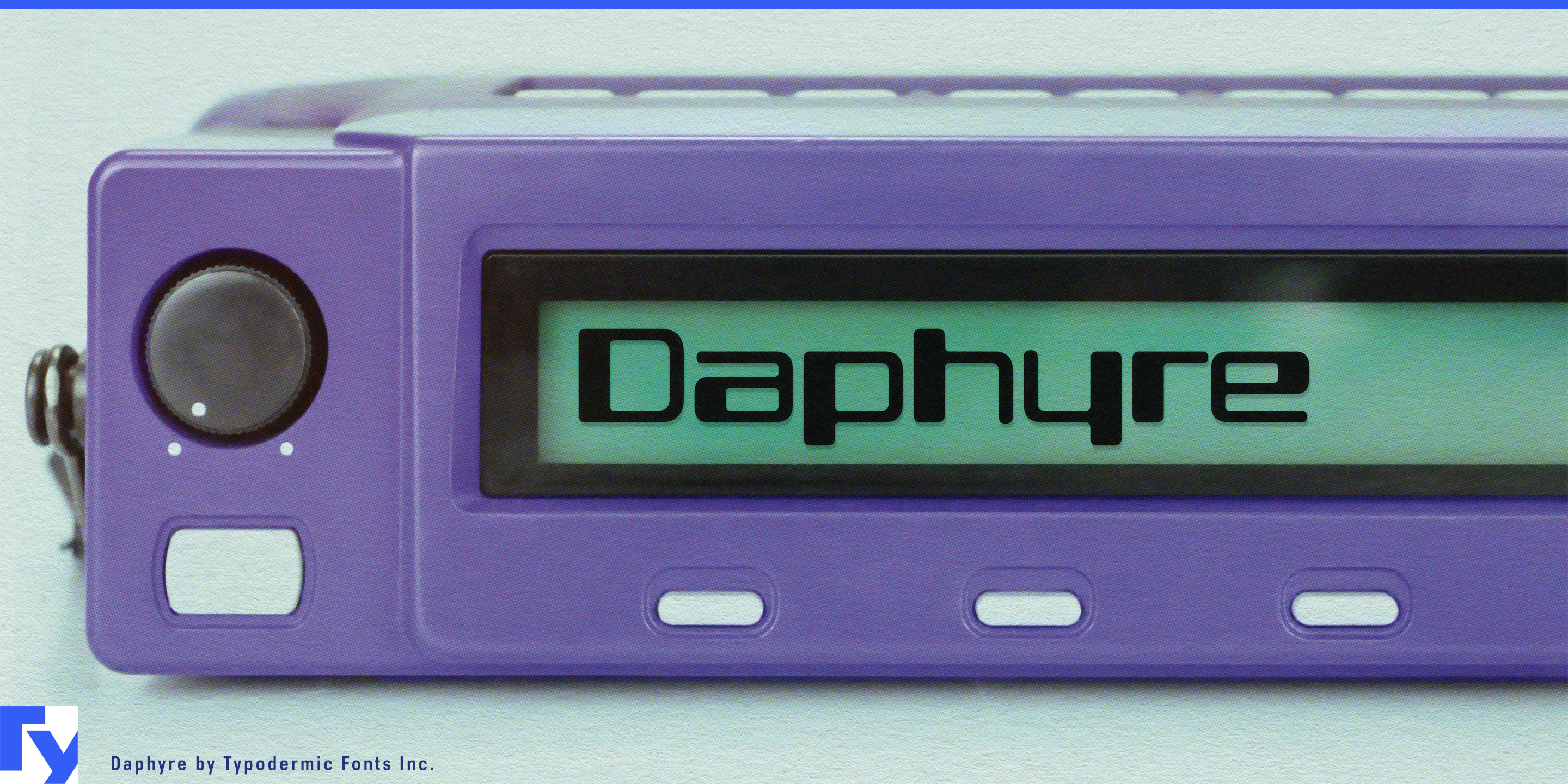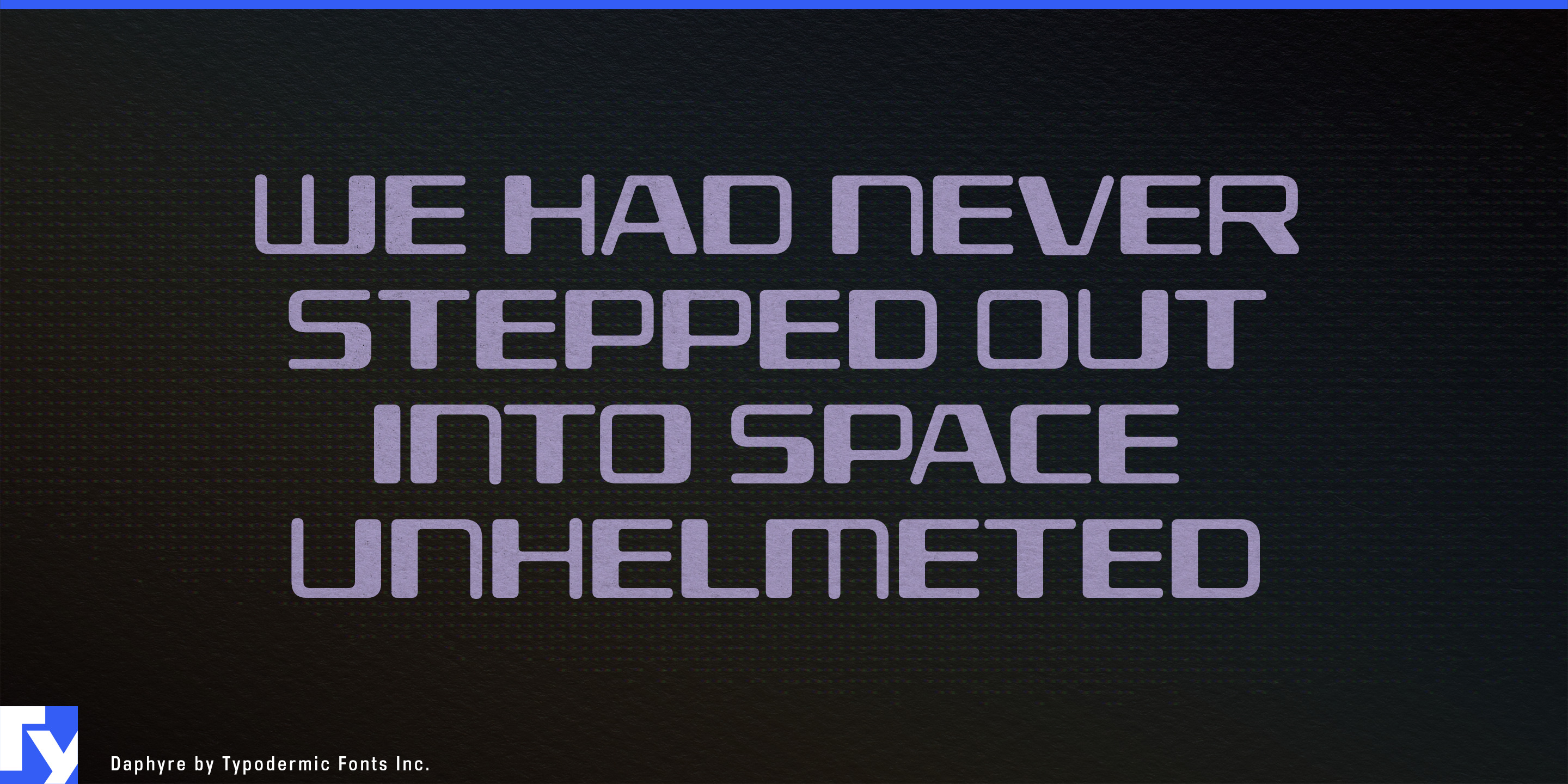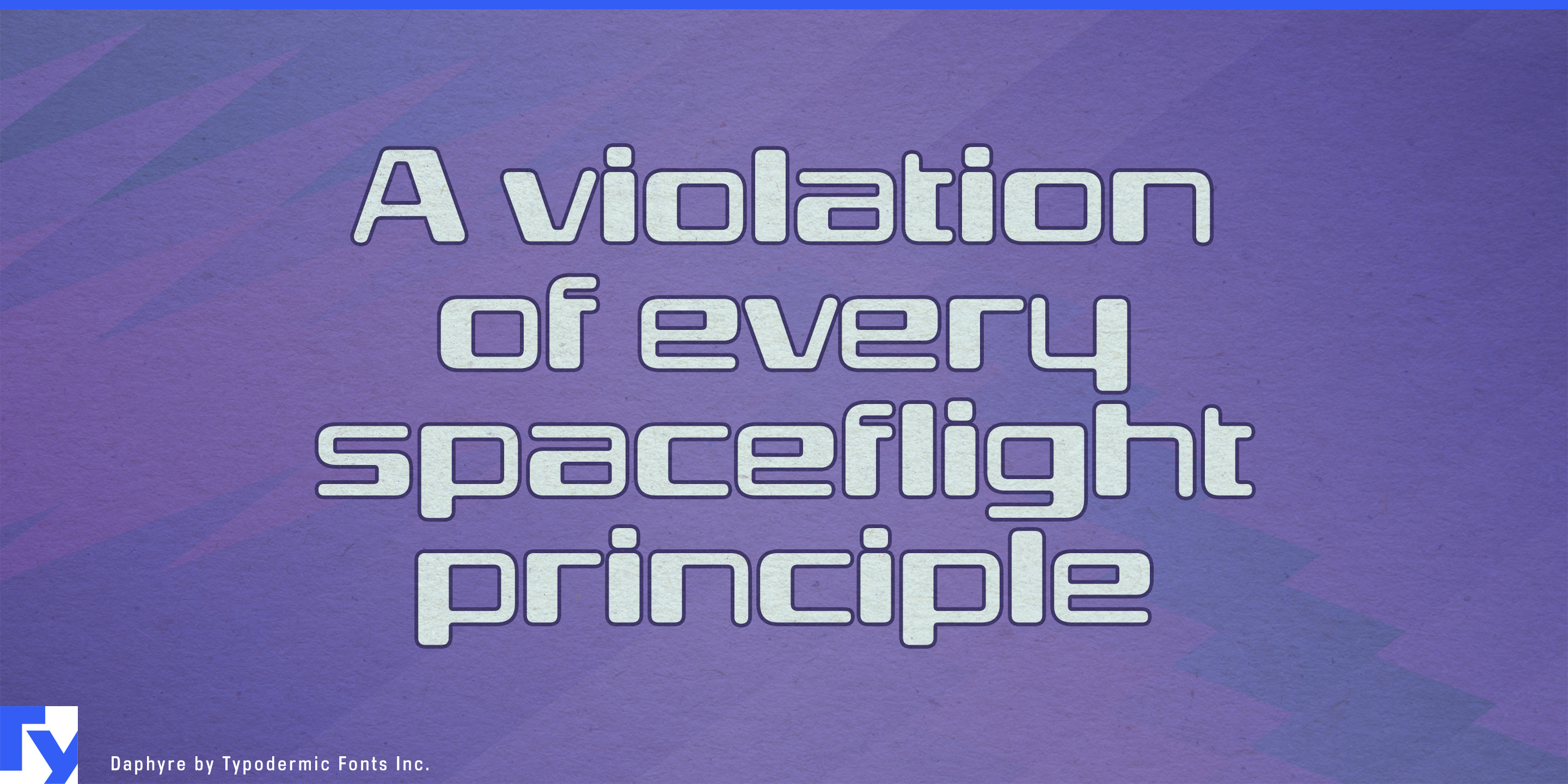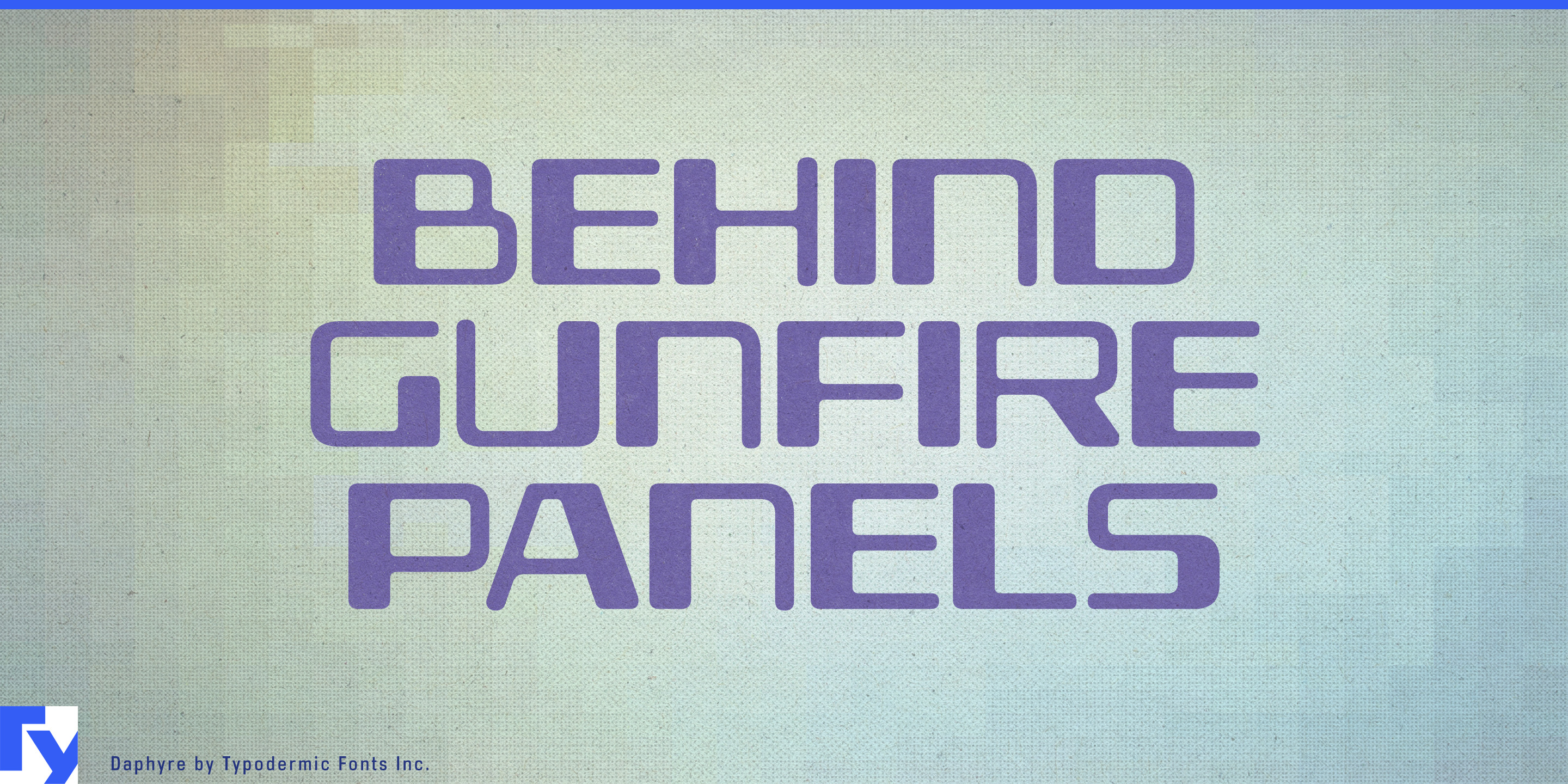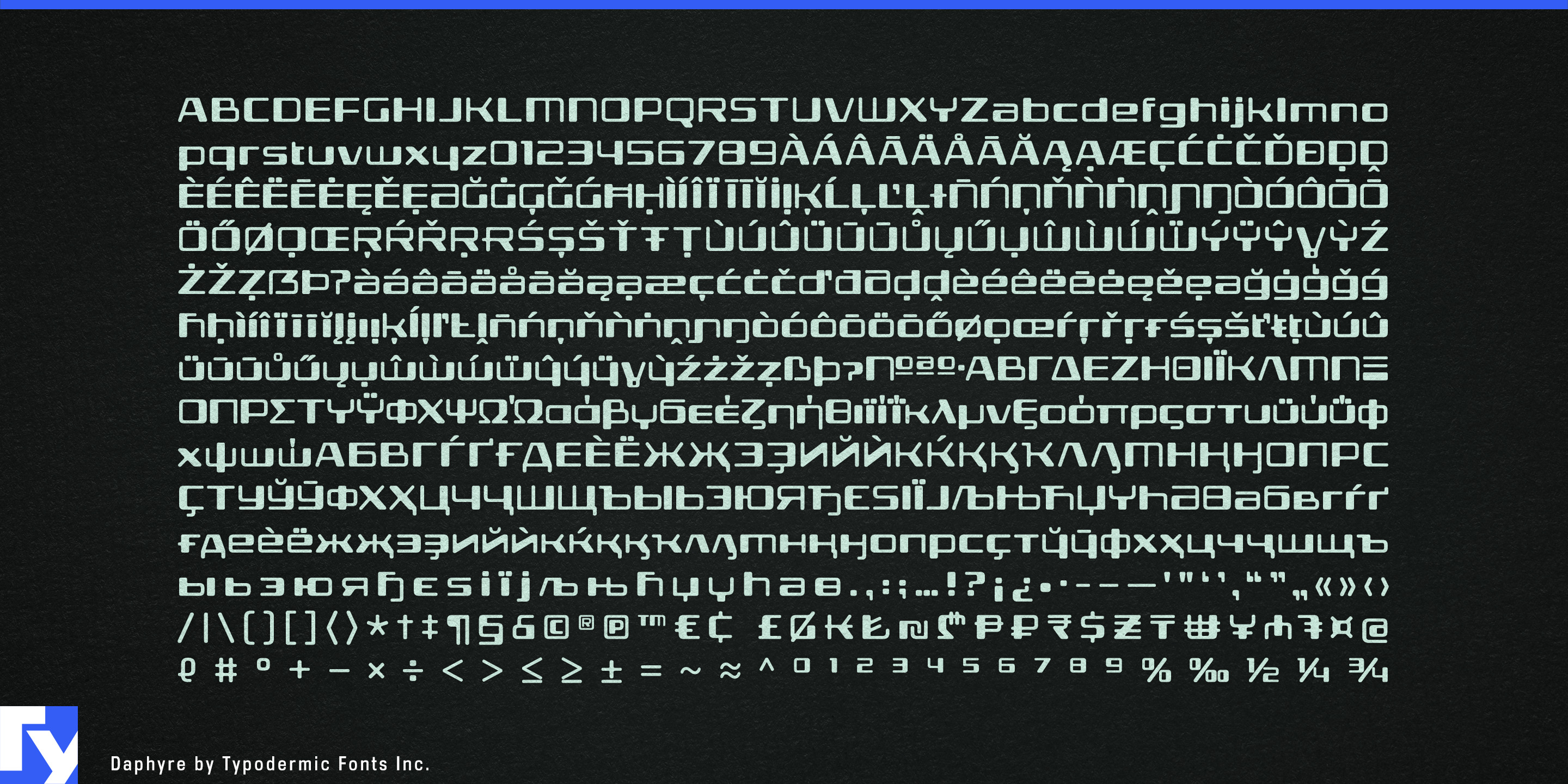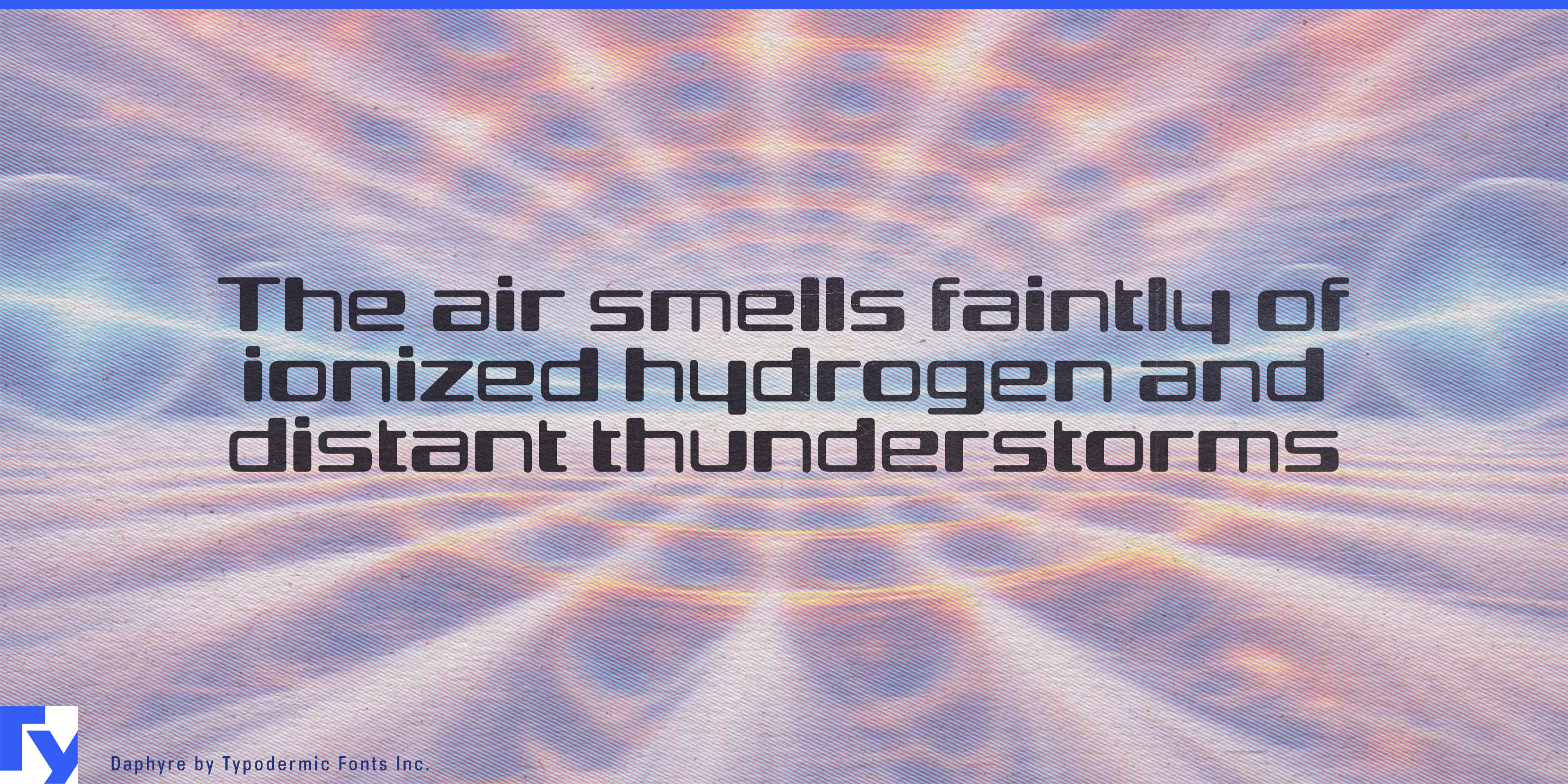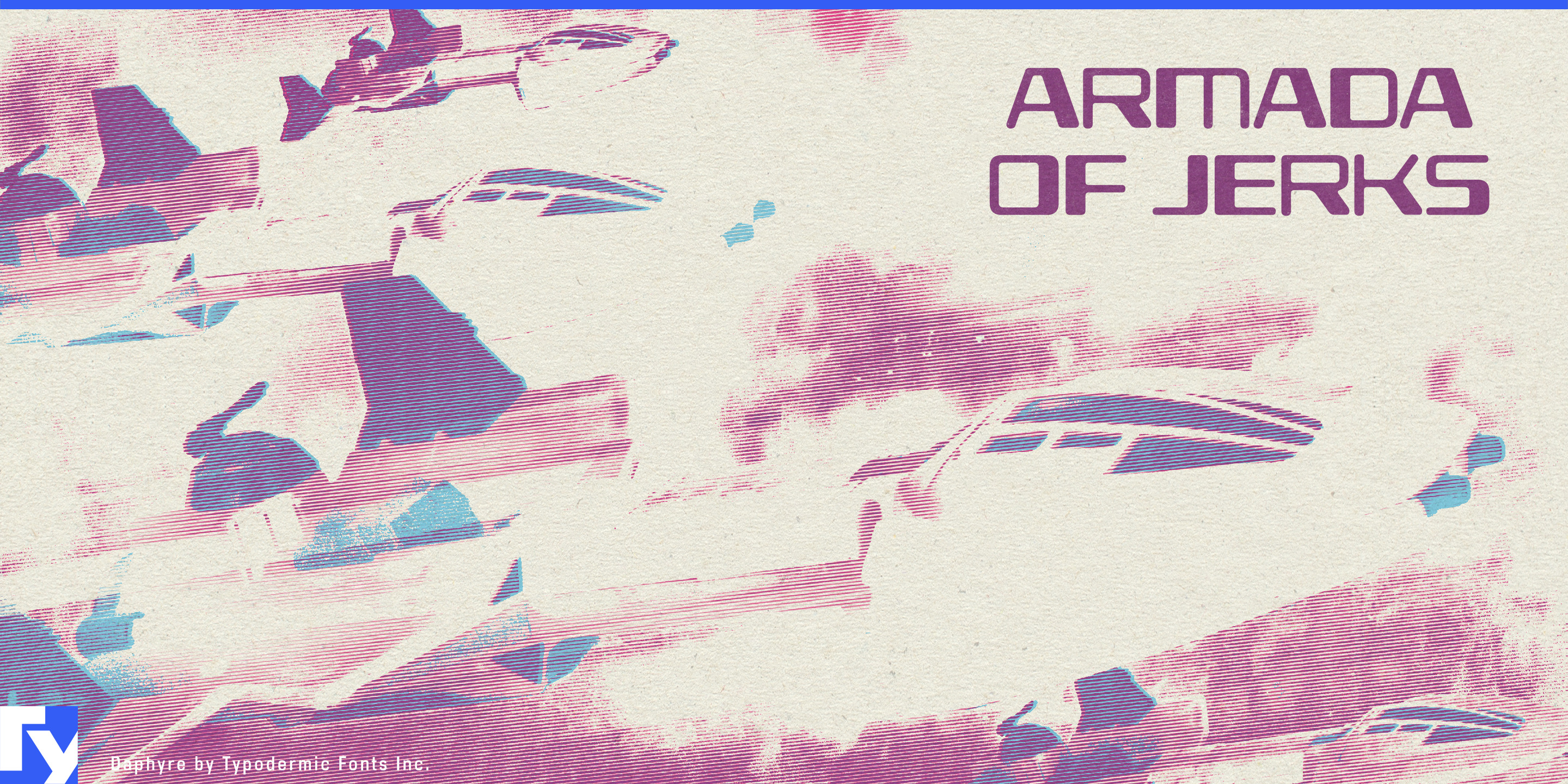
Daphyre
Maschinenlesbare Schrift besitzt eine eigentümliche visuelle Autorität. Daphyre übernimmt einen Teil der vereinfachten Geometrie von MICR-Zeichen und lockert sie zu breiten, offenen Display-Formen. Das Ergebnis vermittelt Scannen, Verarbeiten und Verifizieren, ohne wie die buchstäbliche Schrift auf Schecks auszusehen.
Damit eignet sich Daphyre besonders für Systeme an der Schnittstelle zwischen Mensch und Maschine. Kontaktlose Zahlungskarten, Fahrkarten, vorausbezahlte Tarifsysteme und digitale Ticket-Wallets können die Schrift für Namen von Kartenprogrammen, Markenauftritte für Dienstleistungen und große Beschriftungen einsetzen, während eine konventionellere serifenlose Schrift Kontodaten und Anweisungen übernimmt.
Bei Berechtigungsnachweisen ergibt sich eine ähnliche Rolle. Hotelschlüsselkarten, Mitarbeiterausweise, Besucherpässe, Kongressbadges und Veranstaltungsakkreditierungen enthalten Informationen, die geprüft oder authentifiziert werden sollen. Daphyre kann Organisationsname, Zugangsstufe oder Passtitel tragen und eine technische Note hinzufügen, ohne zu behaupten, die Schrift selbst sei maschinenlesbar.
Paketstationen, Kurierdienste, Gepäcksysteme und automatisierte Abholstationen erweitern die Idee von der Verifizierung auf die Weiterleitung. Inmitten von Strichcodes, QR-Codes und Sendungsnummern eignet sich Daphyre für die menschenlesbare Ebene: Dienstleistungsnamen, Grafiken an Schließfächern und Stationsüberschriften. Garantiekarten, Echtheitszertifikate, Prüfetiketten und nummerierte Beileger können dieselbe visuelle Sprache nutzen, wenn ein Produkt registriert oder verifiziert wirken soll.
Fahrkartenautomaten, Check-in-Terminals, Zugangskontrollstationen und Zahlungsterminals verbinden diese Anwendungen. Daphyre ist auf der Identitäts- und Display-Ebene am stärksten: bei System- und Dienstleistungsnamen sowie großen Überschriften, nicht bei dichtem Interface-Text. Ihr vereinfachter MICR-Anklang verwandelt die Bildsprache der maschinellen Erkennung in eine Display-Schrift für heutige Zahlungs-, Zugangs-, Logistik- und Verifizierungssysteme.